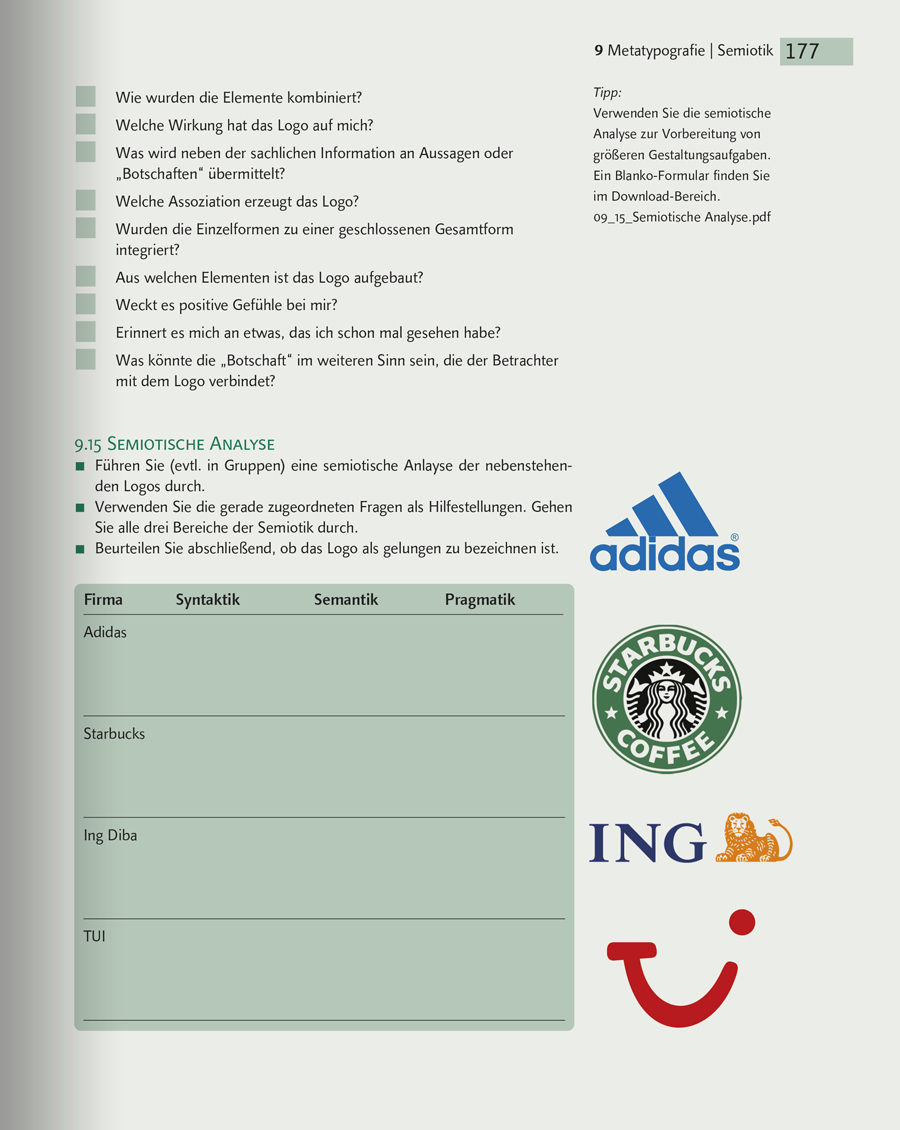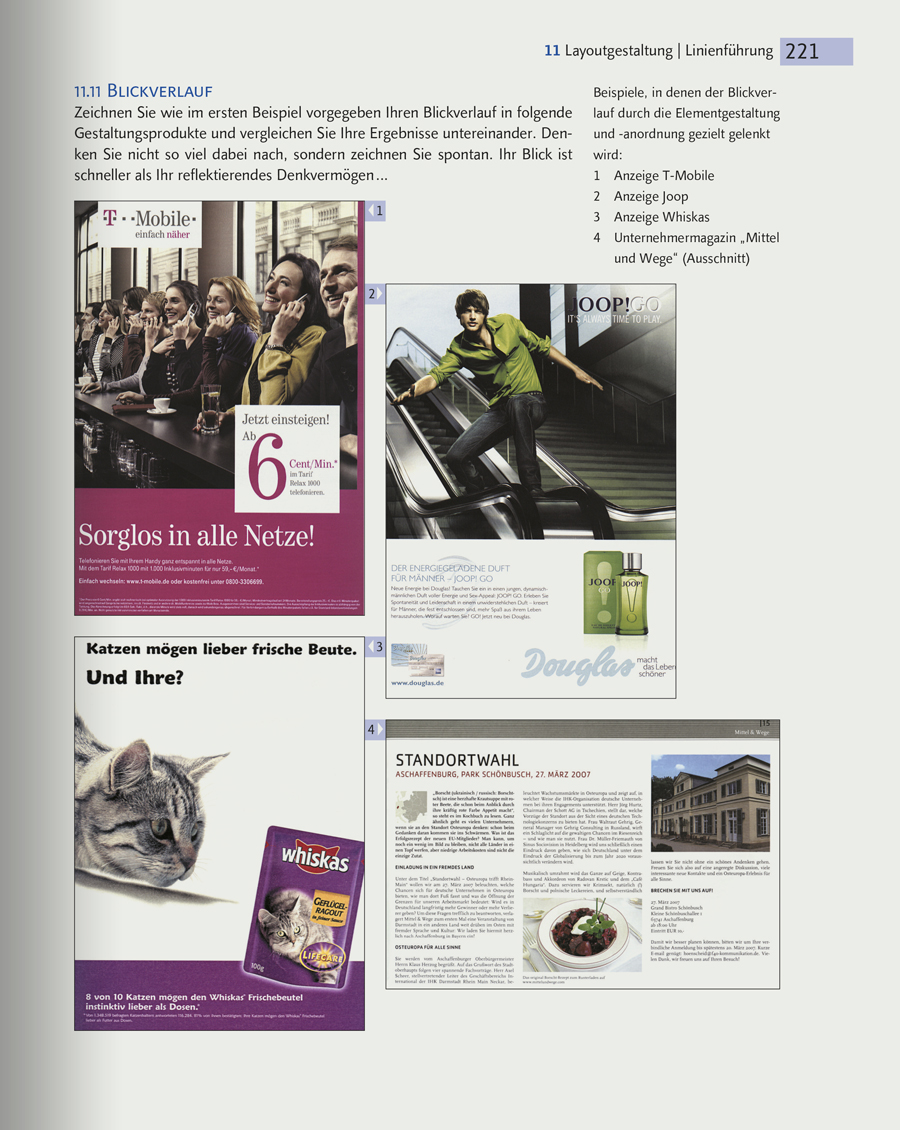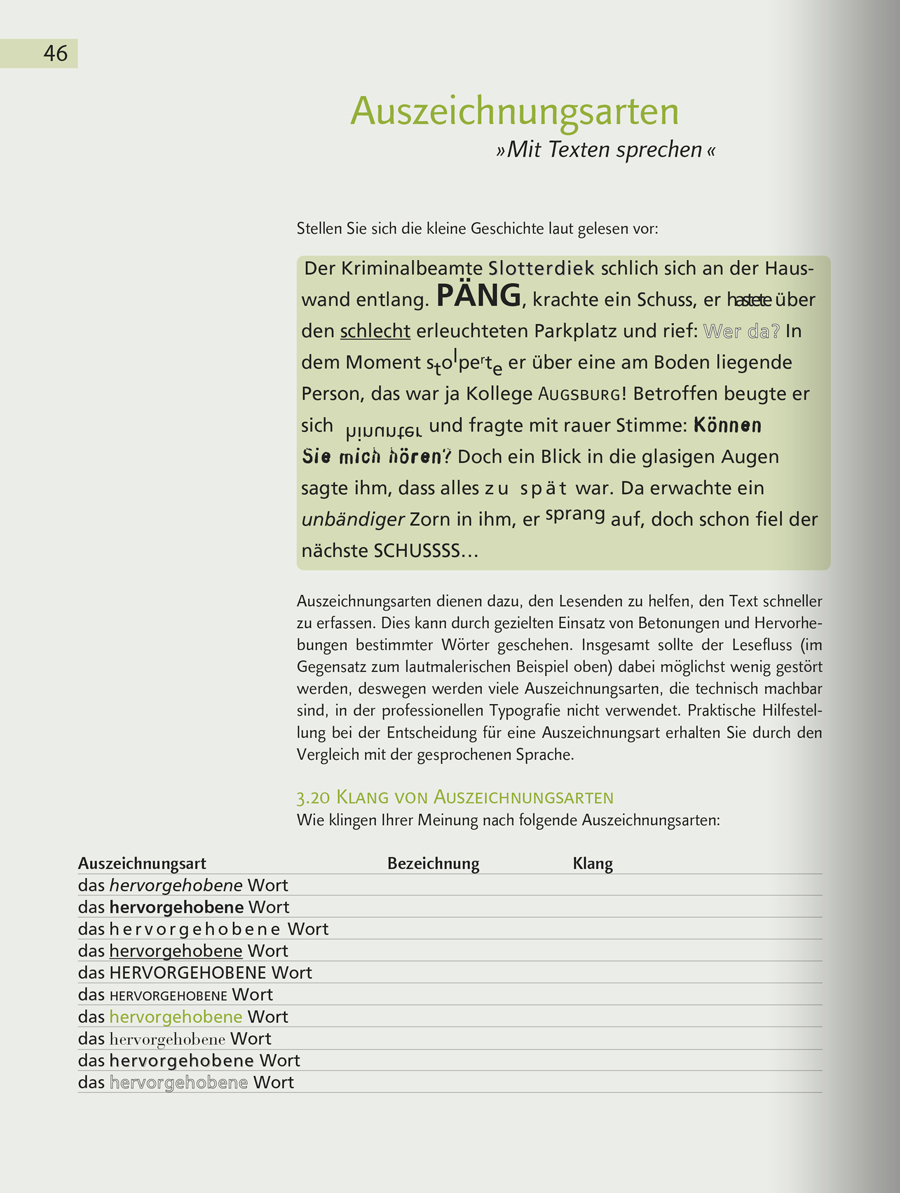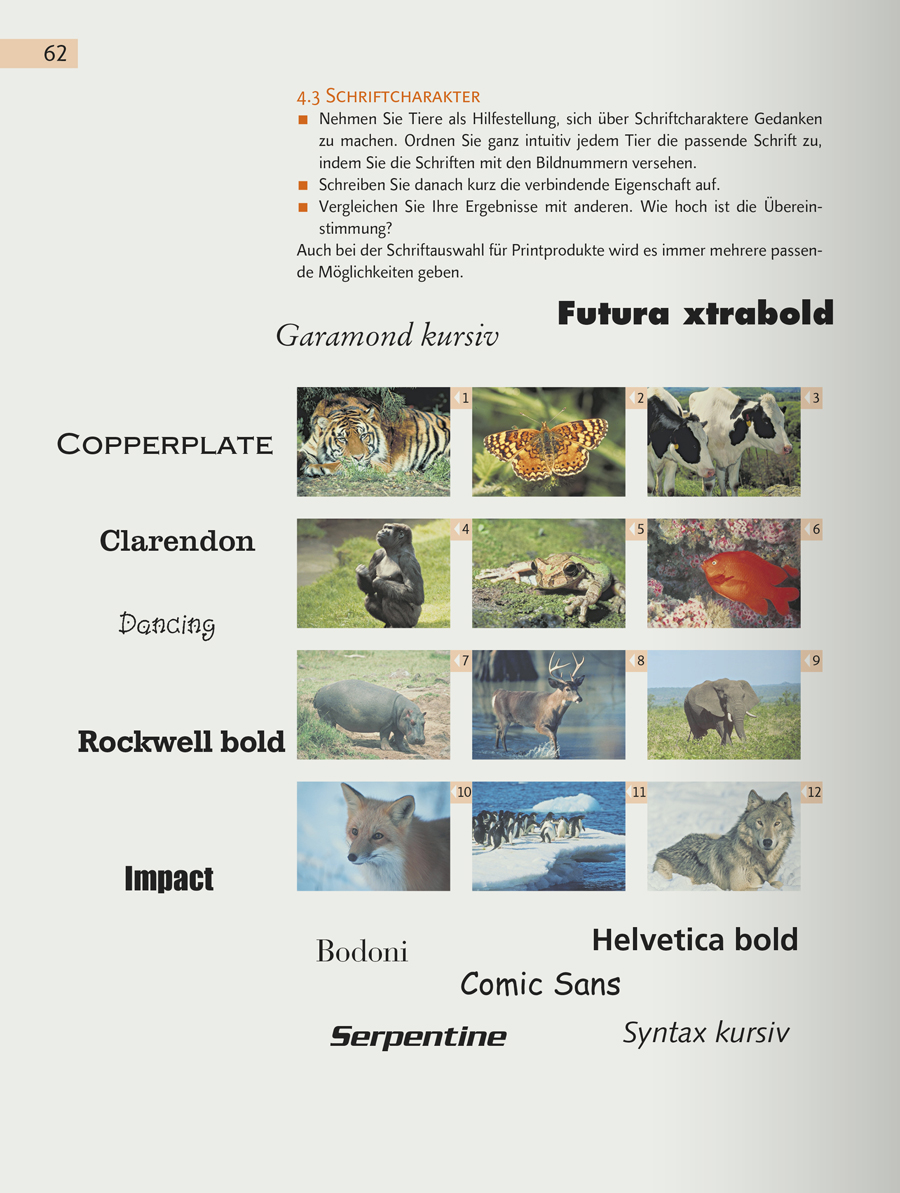
Buchempfehlung: Workshop Typografie & Printdesign von Martina Nohl
Buchvorstellung Workshop Typografie & Printdesign von Martina Nohl
Das Lern- und Arbeitsbuch »Workshop Typografie & Printdesign« von Martina Nohl aus dem dpunkt-Verlag ist die ideale Ergänzung zu Typografie-Workshops und Hochschulseminaren. Aber auch als eigenständiges Lehrbuch weiß es für Typografie zu begeistern. Ich habe das Buch auf einer Publishing-Veranstaltung entdeckt und möchte es Lernenden wie auch Lehrenden sehr empfehlen. Im Gegensatz zu vielen anderen Typografie-Lehrbüchern ist es nicht ausschließlich künstlerisch gestaltet und ästhetisch konzipiert. Es handelt sich viel mehr um ein Lern- und Arbeitsbuch mit echtem Workshop-Charakter.
Typografie-Vermittlung mal anders
Mir gefällt an diesem Buch, dass es einerseits alle klassischen Themen wie Lesbarkeit, Schrift, Seitenaufbau und Layoutgestaltung behandelt. Andererseits, dass es viel Wissen zu den Grundlagen und zur Vertiefung von Typografie und Layout auf eine sehr kreative und motivierende Weise vermittelt. Dadurch erhält die Typografie, die oft als spröde Disziplin empfunden wird, eine spielerische und anregende Erklärung.
Bereits der Einstieg ins Buch hat mich durch die kreative Herangehensweise überzeugt. Zu Beginn geht es darum, sinnliche Buchstaben zu greifen und zu begreifen und um tolle Typo-Art, zum Beispiel selbstgebaute Bilder aus Fruchtgummi- oder Nudelbuchstaben.
Ich empfinde das als eine ungewöhnliche, aber sehr gelungene Lektion zur Wirkung von Schrift und Laufweite sowie zu Schriftausgleich und Schriftmischung.
Fundiert und praxisnah
Aber auch »ernstere« Themen behandelt Martina Nohl in »Workshop Typografie & Printdesign« mit viel Sachverstand und Lehrerfahrung. Zum Thema Seitenaufbau beschreibt sie zum Beispiel detailliert die richtige Anwendung des Grundlinienrasters mit alignierenden Zeilen in unterschiedlichen Schriftgrößen. Verständliche Bildbeispiele vertiefen den Stoff und bilden einen Grundstock für Expertenwissen. Dadurch ist dieses Workshop-Buch nicht nur als Lern- und Arbeitsbuch für Berufseinsteiger geeignet, sondern auch für Design-Profis, die ihre Kenntnisse in Typografie und Print-Design vertiefen möchten.
Für Einsteiger und Profis
Interessant ist das Buch aus dem dpunkt-Verlag daher vor allem für Lehrende an Berufsbildenden Schulen, Hochschulen und für Seminarveranstalter. Die zahlreichen Arbeitsaufgaben, Übungsmaterialien und Anleitungen zu Gesprächsanlässen und Diskussionen sind eine unerschöpfliche Quelle, die ich jedem Lehrenden für die Unterrichtsvorbereitung nur empfehlen kann. Sehr praktisch präsentiert sich auch der Download-Bereich, in dem Bewertungskriterien für Aufgaben und unterhaltsame Typo-Spiele zu finden sind.
Fazit
Alles in allem ist »Workshop Typografie & Printdesign« von Martina Nohl ein motivierendes und kompetent verfasstes Lern- und Arbeitsbuch für die Praxis mit vielen Bildbeispielen und spannenden Arbeitsaufgaben. Ich werde es meinen Workshop-Teilnehmern zur Nachbereitung oder zur Vertiefung von Typografie, Layout und Design am Ende meiner Kurse gerne empfehlen.